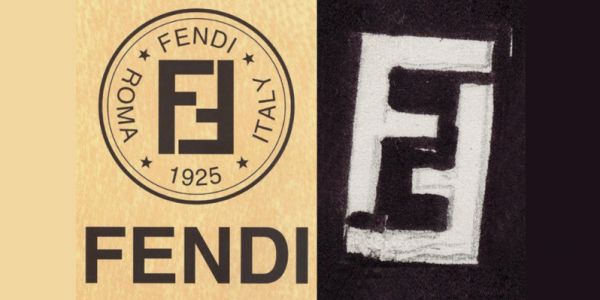
“老佛爷”54年前为FENDI设计的FF标志竟是这个意思!
▲FF Logo是“老佛爷”Karl Lagerfeld 1965年设计。
家族经营让外人加入,自是想要有新方向与作为,卡尔拉格斐动手让FENDI旧时代的皮草改头换面,甩开厚重、没有美感的设计,放胆走出新路,他将皮草重新切割,染上不同颜色,以精湛的工艺做出轻盈的款式,主题是“Fun Fur”,看到这里,FF的意义呼之欲出了。
没错,FF指的是“Fun Fur”(有趣的皮草)。卡尔拉格斐设计了FF Logo,成为代表FENDI的新名词,他曾在接受媒体访问时表示,不是每个人都会念品牌名称,但是Logo大家都看得懂,确实如此,看见FF,一定联想到FENDI,即便是50多年后的今天。
▲2007年在长城办大秀,两旁都是FF Logo。
FF从最初的版本,到1980年代用色块做出改变、1990、2000年左右使用几何图案诠释,期间有高潮有低潮,布满Logo的设计曾经在皮草、包包、配件上大放光芒,又在人们不想要明显Logo的时代,收敛一些。
这几季随着Logo风潮大盛,FF也大鸣大放,2018年FF Reloaded胶囊系列高调宣扬FF理念,2019年再站高峰的Baguette,也与FF密不可分,有浮雕般的图案,或者在背带上招摇,都很吸睛。
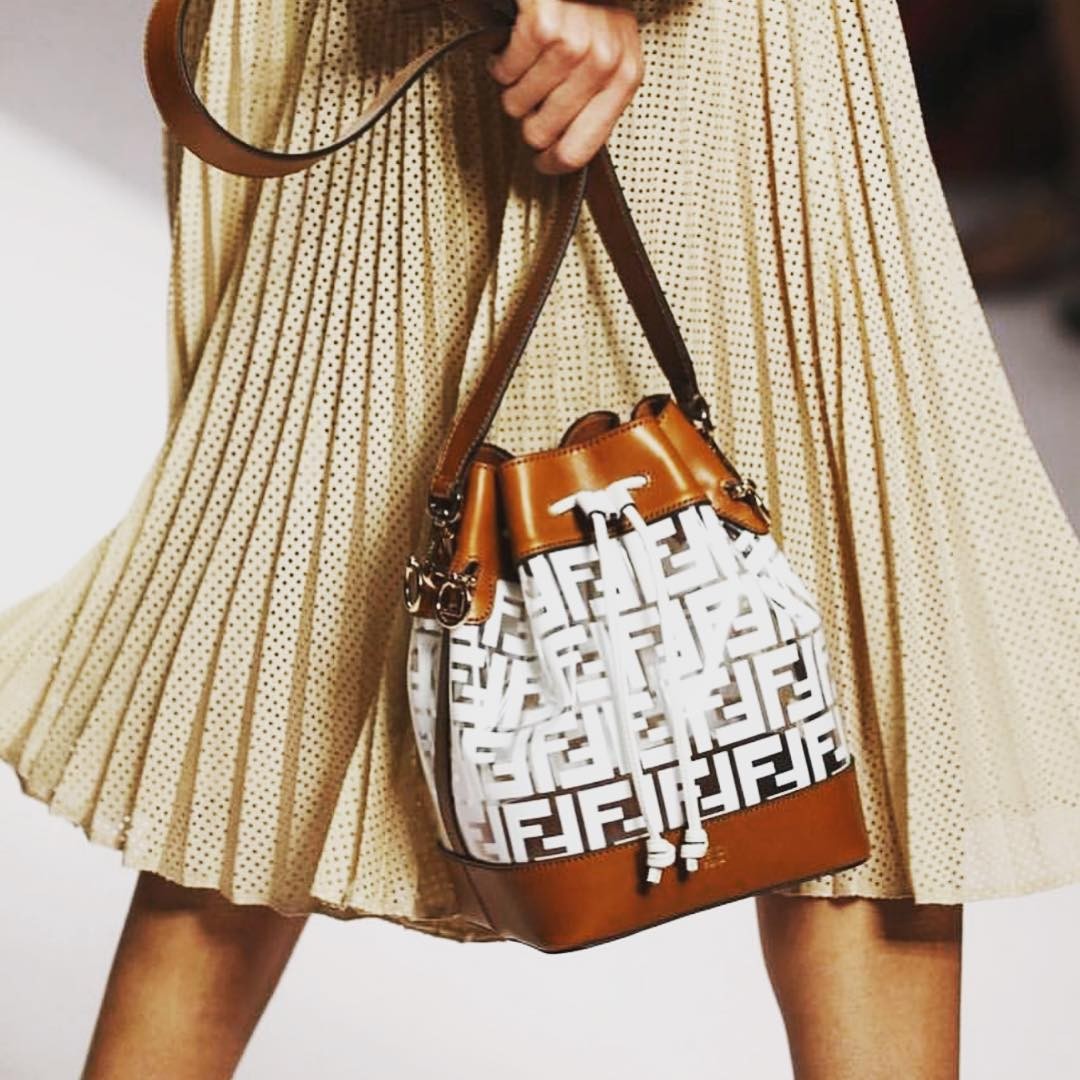
▲FF Logo出现在各种设计上。